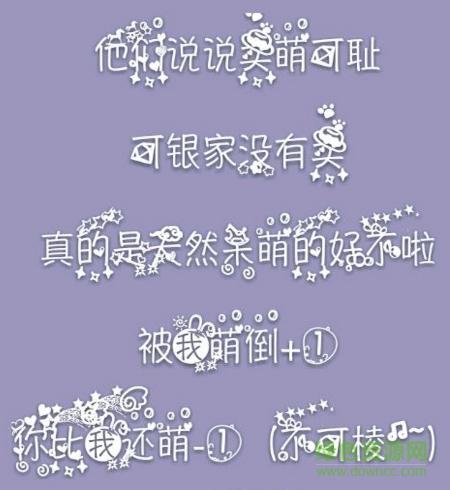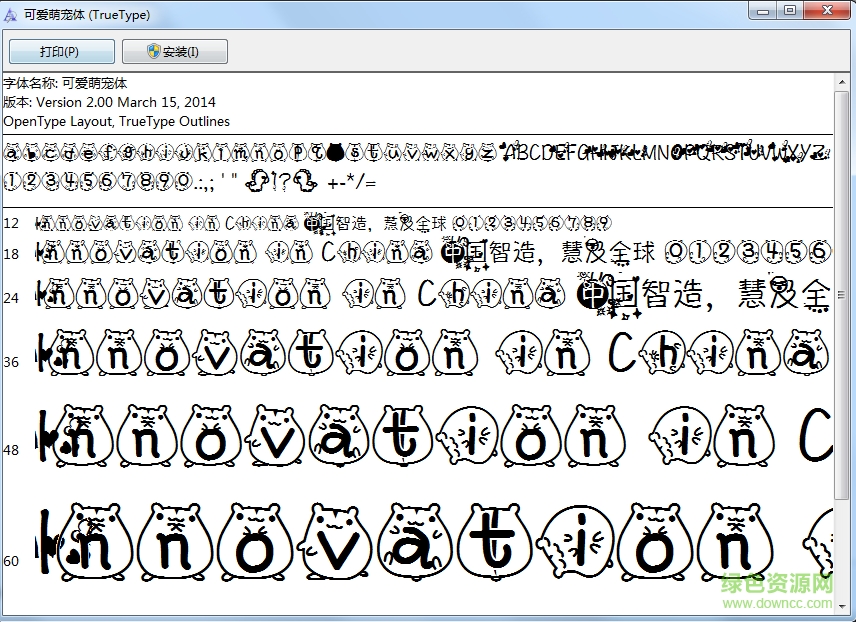
萌寵體是一款超級活潑可愛的卡通字體,各種賣萌的字符點(diǎn)綴,讓文字讓一只只撒嬌的寵物,喜歡的朋友快來綠色資源網(wǎng)吃下這顆安利吧!
可愛萌寵體是一款以POP體為原形進(jìn)行修改的卡通字體,字體間裝飾了有趣的卡通圖案,趣味性十足,喜歡的朋友就下載吧!
萌寵體是一款少女心萌炸的藝術(shù)字體,感受活潑的寵物與你一起跳躍在文字間,英文輸入更是出現(xiàn)萌寵的可愛形狀,快來馬克一下吧!